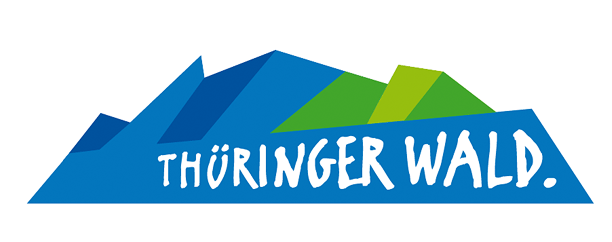
Der Thüringer Wald
… hat ein neues Logo.
Also, ich finde, dem Charakter dieser wunderschönen Mittelgebirgslandschaft wird das Logo leider nicht gerecht. Die im Logo gezeigten Formen erinnern eher an einen kargen, zugige Hochgebirgszug (aus einem Computerspiel mit rudimentärer Grafik) als an die sanft geschwungene Mischwaldlandschaft in der Mitte Deutschlands. Auch die Schrift wirkt auf mich unmotiviert und wenig charmant. Wie schade!
Beim dt gibt es auch den Logovorgänger zu sehen.
Man beachte auch wie gut Typo und Formensprache miteinander harmonieren. Und kalt ist es da, es gibt nur ein paar wenige grüne Flecken. Wahrscheinlich ist es so blau ist, weil hier die Geschmackspolizei reichlich Einfluss hatte. Sollte man glatt ein paar Awards rausholen, dafür, dass man unser schönes Mitteldeutschland so einladend und treffend visualisiert …
Ich finde es traurig, dass bei dieser Neugestaltung die Chance verpasst wurde, der Region ein passendes, ansprechendes und seinem Zweck angemessenes Logo maßzuschneidern. Eine solche Aufgabe ist doch für jeden Corporate Designer ein echter Traum und ich finde es immens schade, dass das Ergebnis neben den handwerklichen und inhaltlichen Mängeln so furchtbar lieblos wirkt.
Leider spielt nicht immer nur Konzeptionsstärke und liebevoll hochwertige Gestaltung eine Rolle. Da geht eben auch oft viel (zu viel) über Beziehung … ist ja auch ehrenwert dass die Aufgabe nicht zu den großen Metropol-Agenturen gegeben wurde, sondern wenigstens in der Region blieb. Aber selbst da gibt es doch sicher …
Hier noch Hintergründiges von den Kollegen: Aktuelles von ART-KON-TOR – neue Marke "Thüringer Wald" wird gelauncht
Okay – Idee und Konzept sind vielleicht gar nicht mal so übel. Aber die Umsetzung … und wie Du schon sagtest, typisch ist es auch nicht. Die spitzenübersäte Silhouette passt dann doch eher zu Südtirol. Selbst da wirkt diese nicht so aggressiv. Und dass man hier mit Perspektive noch ein drauf setzen wollte, ging dann so völlig nach hinten los. Wirklich jammerschade!
Ich könnt’ jetzt paar Entspannungs-Buchstaben-Kekse und zwei Augen-Trostpflaster von Dir gebrauchen.
wir erhoffen uns mit dem neuen Logo positive Impulse für den Tourismus.“ so Andreas Trautvetter, Präsident des Regionalverbundes Thüringer Wald.
Wer meint, dass die Touristen wegen eines Logos kommen, der hat kein anderes verdient.
Die grün-blaue Farbgebung vermittelt zwischen bisherigem Erscheinungsbild der Regionalmarke Thüringer Wald und dem Markenauftritt des Landes Thüringen.
Da wollte jemand einfach zuviel in einem Logo unterbringen. Mit dem Anspruch kann man nur scheitern. Anfängerfehler.
Die in der Formensprache visualisierte Kantigkeit und Kernigkeit spiegele zudem nicht nur die Region mit seinem Mittelgebirge in der Mitte Deutschlands wieder, sondern reflektiere auch seine Menschen, wie es die verantwortliche Agentur ART-KON-TOR augenzwinkernd beschreibt.
Solche Thüringerinnen mit der Mentalität eines Eisberges gibt es wirklich. :-|
Mein thüringer Kollege ist genau solch ein Kantholz, insofern passt das Logo gut zur Mentalität. Aber ob man potentielle Besucher schon vorher darauf hinweisen muss?
Ich kenne aber viiiel mehr charmante Thüringer als solche, die durch einen kanthölzernen Eisberg repräsentiert werden müssten. ;-)
Na klar. Die Leute werden jetzt in den Thüringer Wald strömen, um die Thüringer Gletscher zu sehen.
Ich kenne ja auch nur diesen einen ;-)
Das ist die FF Erikrighthand von Erik van Blokland und hat auch schon einige Jahre auf dem Buckel.
... die hat sich in mein Hirn schon dermaßen als Bäckertüten-Schrift eingefressen, dass ich mit dem Eisberg im Hintergrund fast schon an Tiefkühlbrötchen denken muss :roll:
Ja stimmt, die habe ich kennengelernt, als ich während meines ersten Designpraktikums zum allerersten Mal in meinem Leben eine Schriftensammlung durchforsten durfte. :nicken:
Im Zusammenhang mit dieser Bildmarke empfinde ich die Schrift aber wirklich als unpassend. Die Formensprache und Anmutung von Wort- und Bildmarke bricht für meine Begriffe völlig auseinander. Die Bildmarke ist glatt, reduziert, technisch, kantig und kalt in der Anmutung. Die Schrift imitiert eine Handschrift, ist rau und wirkt unbearbeitet, mal eben so hingeschrieben, nicht raffiniert oder kalligrafisch, nicht technisch. Solch ein Bruch kann gewollt sein, kann einen Zweck erfüllen, aber ich tue mich schwer, ihn in diesem Fall als gelungen anzuerkennen. Mit viel gutem Willen könnte man rauslesen, dass die Bildmarke Modernität ausstrahlen soll und, dass sich Thüringen, „stylemäßig“ gesehen auf der Höhe der Zeit befindet, während der Schriftzug das dann wieder relativiert und sagt: „Ach na ja, aber in echt sind wir auch handgemacht und freundlich – kommt uns doch einfach mal besuchen!“
Warum denn? Gibt es in den neuen Bundesländern keine gewachsene Wappentradition, derer man sich (als Inspirationsquelle und in abgewandelter Form) bedienen könnte? Darauf wäre ich jetzt gar nicht gekommen …
Die eigene Erfahrung lehrt mich, dass derartige Logos allenfalls von Designinteressierten wahrgenommen werden. Die potentiellen Touristen lassen sich eher von Inhalten überzeugen (gibt’s in der Region einen Baumwipfelpfad, Spaßbäder, Konzertsaal, Thermen usw.) als von einem Logo abschrecken. Damit wäre ich bei der Agentur-für-oder-gegen-Redesign.